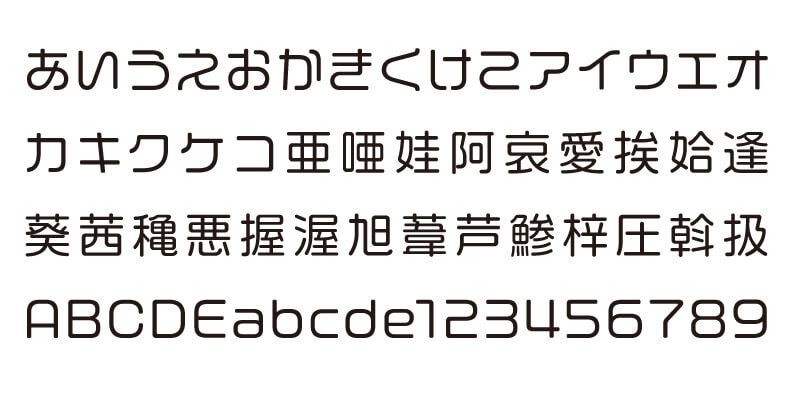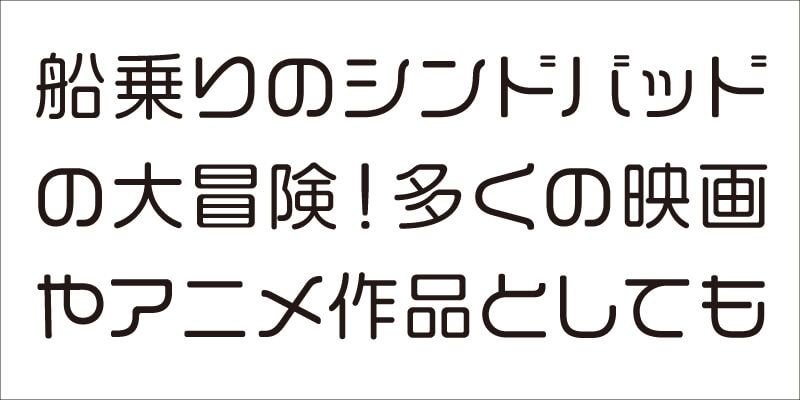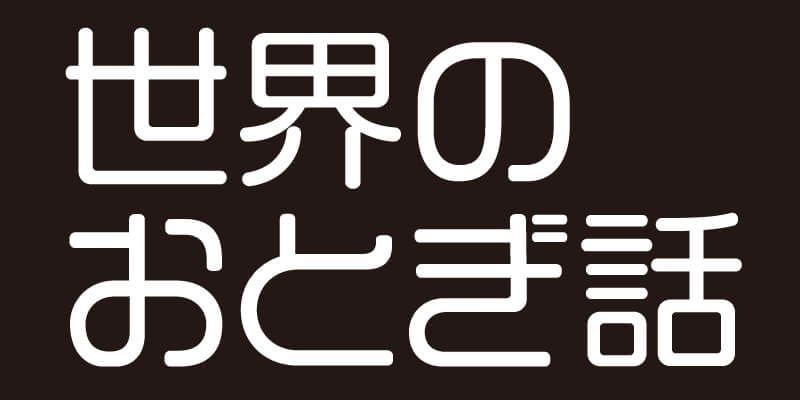
Nacido de VDL-LogoJr y caracterizado de forma similar por sus vivas formas de carácter, VDL-LogoMaruJr es un tipo de letra gótico redondeado (sans-serif) con una naturaleza más “gráfica” y un sabor moderno.
Visual Design Laboratory (VDL) cree en equilibrar la belleza natural de las formas de las letras con estándares rigurosos de legibilidad. VDL ofrece una completa colección llamada “VDL Designers Fonts” (VDLデザイナーズフォント), que seguro va a resonar con diseñadores que buscan un tipo de letra muy individual manteniendo un gran atractivo.